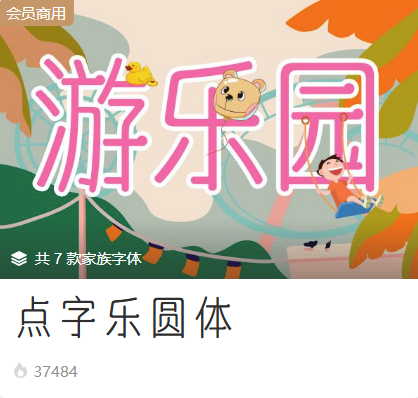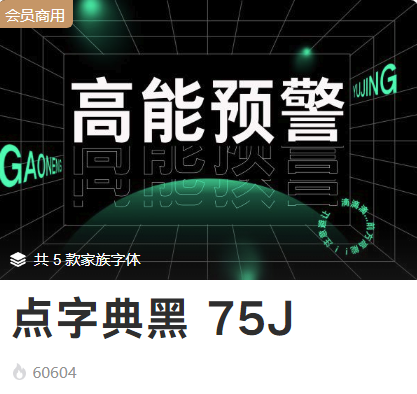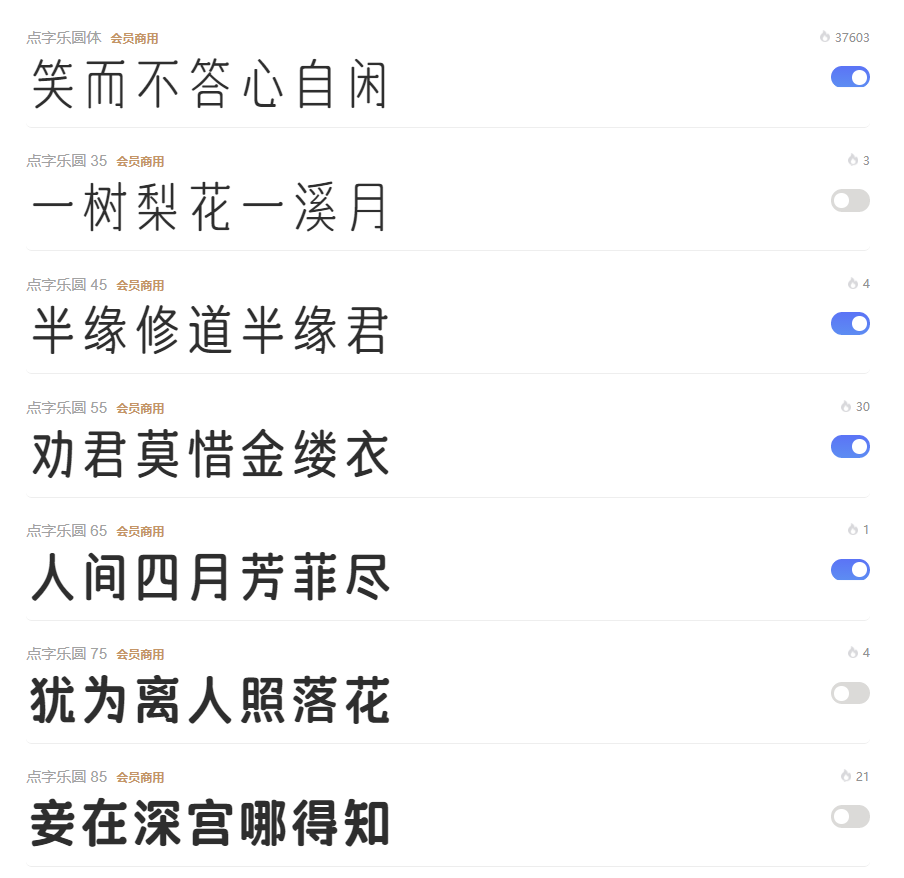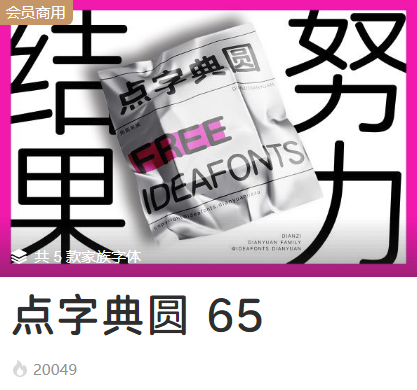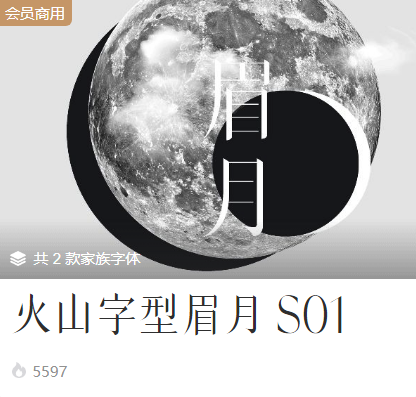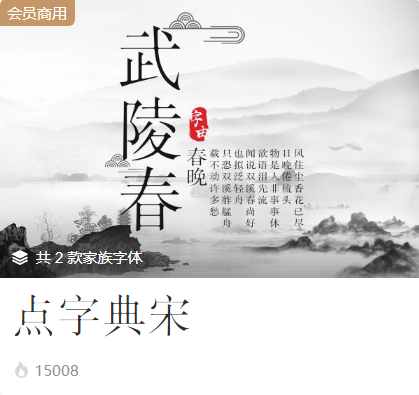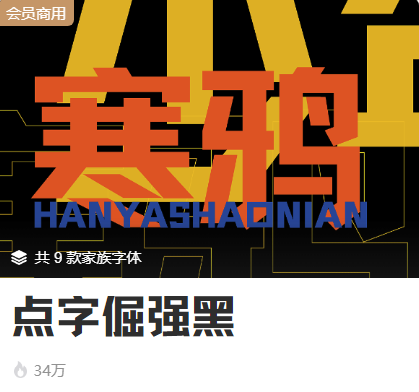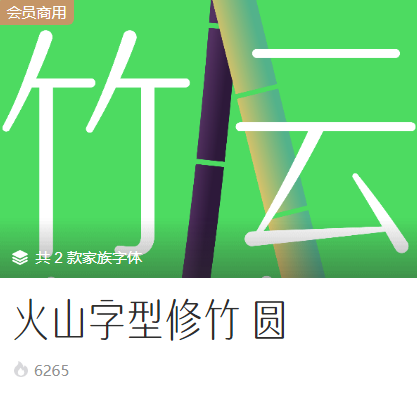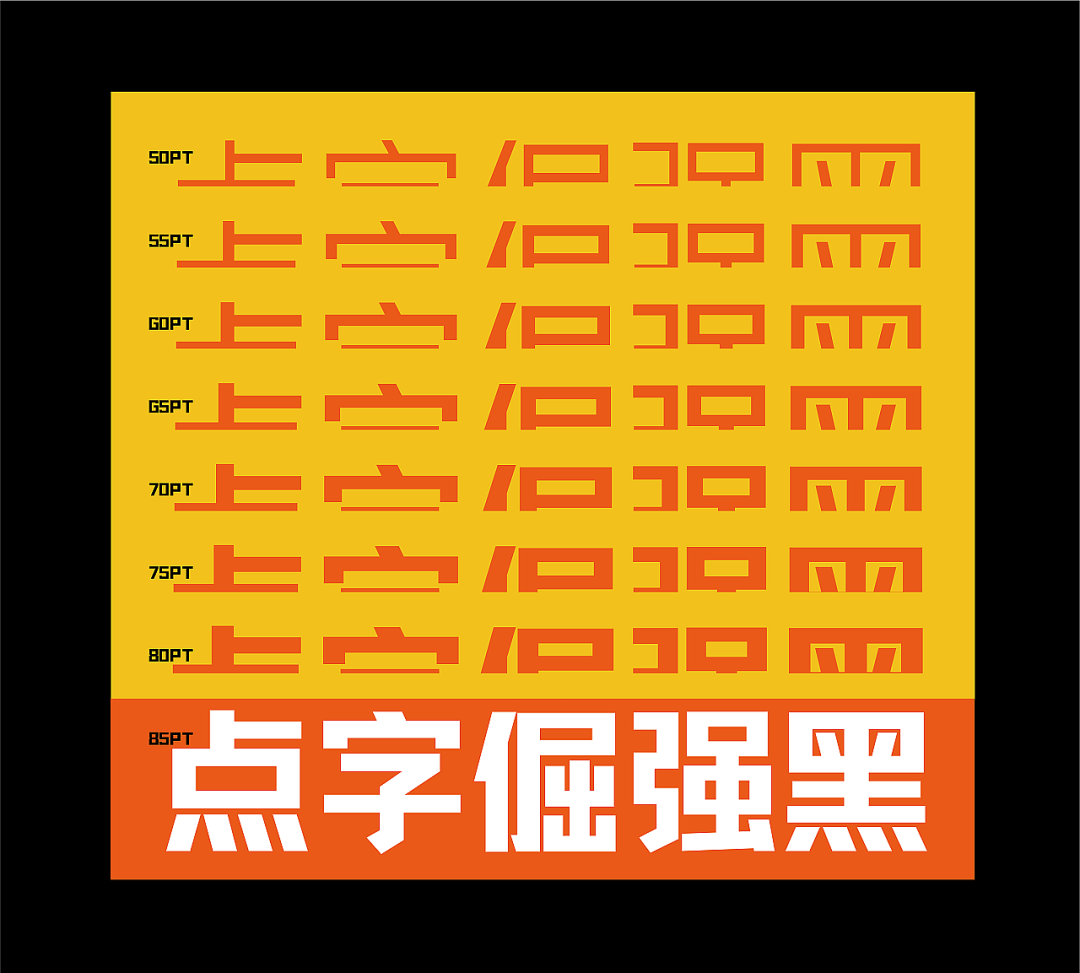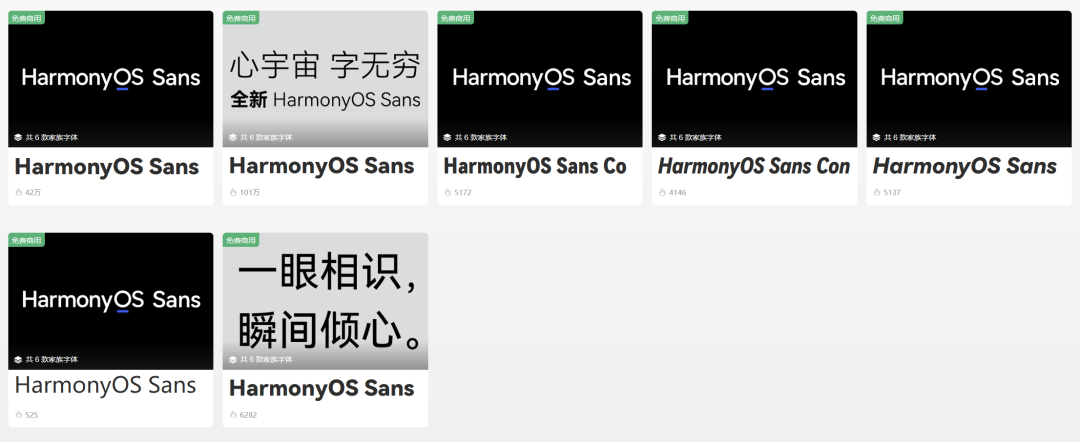
盘点那些家族字体,一家人就要整整齐齐!
这几天字由又上了一款家族字,没错,就是你们很熟悉的点字乐圆体。
一共有7个字重,无论是用在仪式感的画面,还是展示甜蜜可爱的感觉,都拿捏到位~
其实2021还上了很多家族字,比如点字典圆,点字典黑,各有5个字重。
还有点字典仿宋、点字典楷、点字典宋、火山字型眉月、火山字型修竹,都分别有2个字重。当然还有我们的明星字体,点字倔强黑,一共有9!个!字!重!
除了会员字体,免费字体也有很多新家族,比如小米刚刚发布的MiSans,一共10个字重,包含29,093个字符,支持多种语言。跟它类似的,还有今年五月发布的阿里巴巴普惠体2.0 ,新增了4个字重,一共9个字重。至于六月横空出世的HarmonyOS Sans,我已经数不清它有多少个字重,多少种语言了,总之就是牛上天了!不光基础字型,爆火的锐字真言体,也在今年扩充了家族——锐字潮牌真言简2.0,一共有6个字重。当然字由上的家族字远不止这些,如果还想发现更多,可以在官网或客户端筛选多字重。